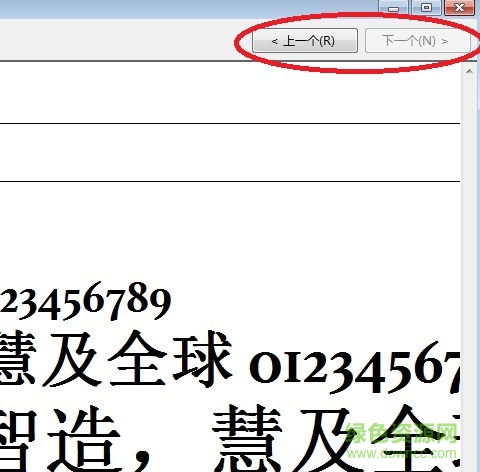
athelas bold
athelas bold 字體是一款經(jīng)典的英文字體,字體點畫呼應(yīng),結(jié)構(gòu)輕巧,線條雖粗又不失秀美,辨識度高,有需要者歡迎在綠色資源網(wǎng)下載!
athelas bold簡介:
athelas bold字體
字體造型規(guī)整,富于力度,給人以簡潔爽朗的現(xiàn)代感,有較強的視覺沖擊力,這種個性的字體,適合于機械科技等主題。